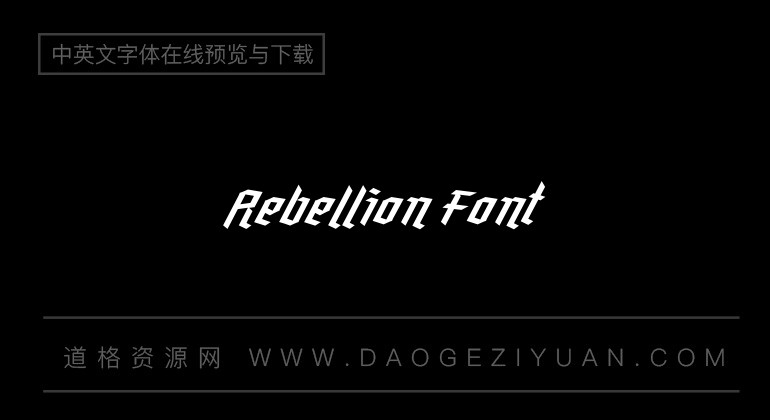
Rebellion Font是一种英文字体,它具有粗犷和独特的设计,适用于各种设计项目。该字体由Jonathan S. Harris于2010年创建,它受到了电子游戏、街头艺术和重金属音乐等各种文化形式的启发,因此它的设计风格也充满了这些元素。 这种字体具有很高的辨识度,因为它的字母形状都非常独特。字母的线条很粗,边缘有锐利的角度,并且字母之间的间距也比较紧凑。这种设计风格使得Rebellion Font非常适合于需要强烈的视觉效果的设计项目,例如海报、书籍封面、音乐专辑封面、标志和品牌标识等等。 总的来说,Rebellion Font是一种充满个性和创意的字体,它可以帮助设计师在他们的项目中增加一些独特的风格和视觉冲击力。内容介绍
Rebellion Font是一款非常不错的手写艺术字体,具有很好的视觉感,适合于文化类的宣传设计、商业类品牌的广告和产品包装设计以及个性化文字排版等较多场景。